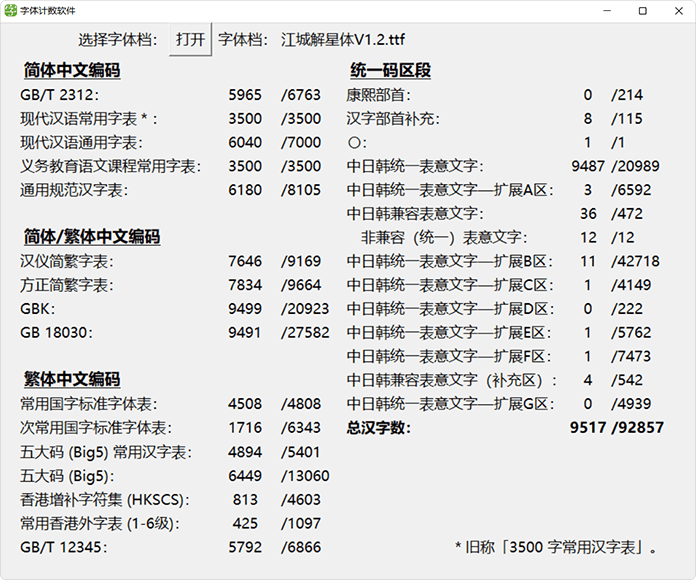
猫啃网之前转载了一款日本的解星系列字体,解星系列不同于传统的印刷,通过在右侧添加加圆型衬线,使字体左右更加平衡,同时也为字体添加了不一样的特色。
但是解星系列字体是日本的一款开源字体,其制作的汉字部分主要是依据日本的JIS水准,所以简体字型较少,我们中国大陆的小伙伴们使用起来缺字较多,十分可惜。有见于此,我们的江城系列大佬@刘鹏开启了解星字体补字计划,开始了漫漫长路的补字旅程。
目前,江城解星体已经完成现代汉语通用字表(旧称3500字常用汉字表)的补字,再加上原来解星系列已有的简体字部分,已经有5498个简体字,能基本满足大陆的小伙伴一般的使用需求了,于是决定在猫啃网上先发布一个版本以仅大家使用。后续会继续缓慢补字,预计会做完GB/T 2312标准系列字体。
Ver 1.3(2022/07/30)
- 修改错字:逸沱埝谂锛徭摇瑶谣謡遥鳐鹞繇琢捩
- 优化字型:脊㐅杀
- 新增字型:戾绥纨纩纾绀绁绂绋绌绔绛绠绮绱绶绺绻绾缁缂缃缇缈缋缌缏缑缒缗缛缟缧缬缯缲缳烯烀炷焖焯焱煳煨煅煸煺熘熵熠墒硒谧籴倴喯捹渀錛餴傜嗂媱愮暚榣滛熎猺磘鎐颻飖鰩
Ver 1.2(2022/03/28)
- 增补了475个字
- 修复了错字:倏骚
- 优化了若干字形
Ver 1.1(2022/03/01)
- 修改了合并丢失笔画的字
- 增加了64个字
Ver 1.0(2022/02/27)
- 江城解星体第一版正式发布。